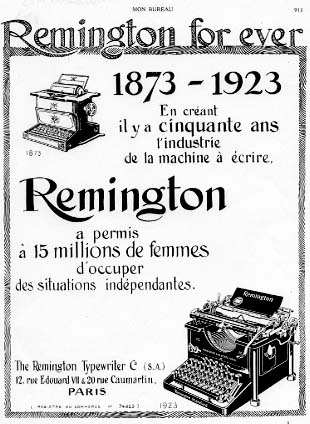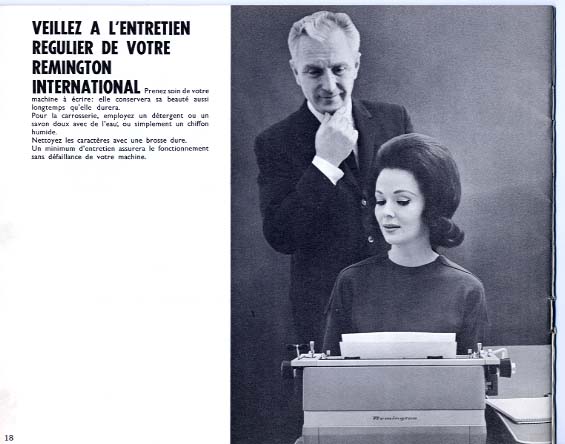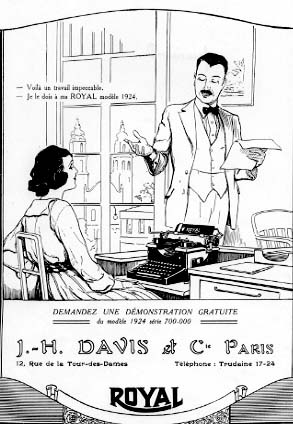
Pour apporter ma pierre à cet intéressant débat.L'accent de Marseille, Lyon, Paris, Québec, Berne, Bruxelles, Dakar et autres contrées tombe aussi bien en bas de casse qu'en capitales (nationales, régionales voire locales).
Doit-on s'en plaindre ? Faut-il le restituer graphiquement ? Existe-t-il un moyen de ne pas respecter l'omerta de la lecture pour soi ?
…En ce qui me concerne, j'accentue ou non selon… le client et ma fatigue ;-). Le correcteur (homme ou logiciel) n'est généralement pas assez vigilant pour corriger toutes mes fautes de composition et renonce.
-- Comme souvent je reçois des poulets du genre :"ce message est volontairement redige sans accent. Pour etre compris de tous"
Je suis alle vendredi au palais des congres de Montpellier. Il y etait question de sante et de travail. Une affiche annoncait fierement : 5ieme COLLOQUE SANTE ET TRAVAIL - LA PREVENTION DES RISQUES PROFESSIONNELS. Le tout dans un accent languedocien a couper au couteau mais sans accent sur les majuscules. Personne ne s'en est offusque. Je doute même que quelqu'un d'autre y ai prete attention.
A noter : Le plomb est maintenant interdit dans la plupart de ses usages traditionnels.
-- Question, si les accents sont facultatifs sur les capitales, pourquoi les maintenir en bas de casse ?
J'ai entendu (et lu) diverses raisons pour maintenir cette coquetterie ou pour s'en passer. Les plus grands auteurs ont ete appele a la rescousse : grevisse, hyene, academie, Remington (ce dernier en collaboration avec Colt pour descendre les ornements disgracieux).
J'ai entendu (lu) que les accents devaient être maintenu s'il existe une embiguite possible : Palais des congres est donc un mauvais exemple qui a entendu parler d'un original qui aurait baptise son restaurant comme ca ?
J'ai entendu (lu) que seules les "Majuscules initiales" étaient exemptees de port d'acccent : A chaque fois. Eve. Etage…
J'ai entendu (lu) que tout doit etre accentue.Je ne sais a quel saint me vouer : la maternelle nationale qui proscrit l'accent initial, ma maternelle qui s'en fiche ou le lait de l'orthotypo que je tete depuis quelques annees ?
Pour le plaisir : une publicité pour la machine à écrire "Royale" avec accent sur les majuscules (1924) et une publicité pour la Remington où la difficulté est tournée (1923) et sans accent sur les majuscules (1960 ?) .